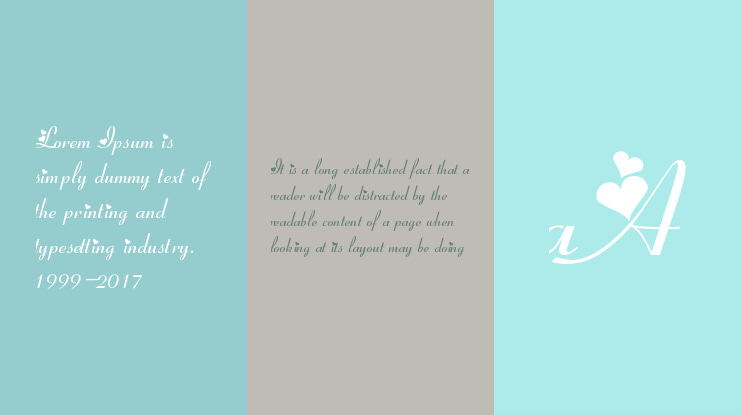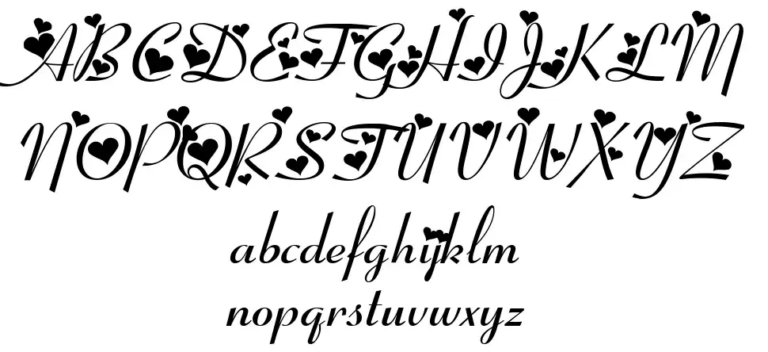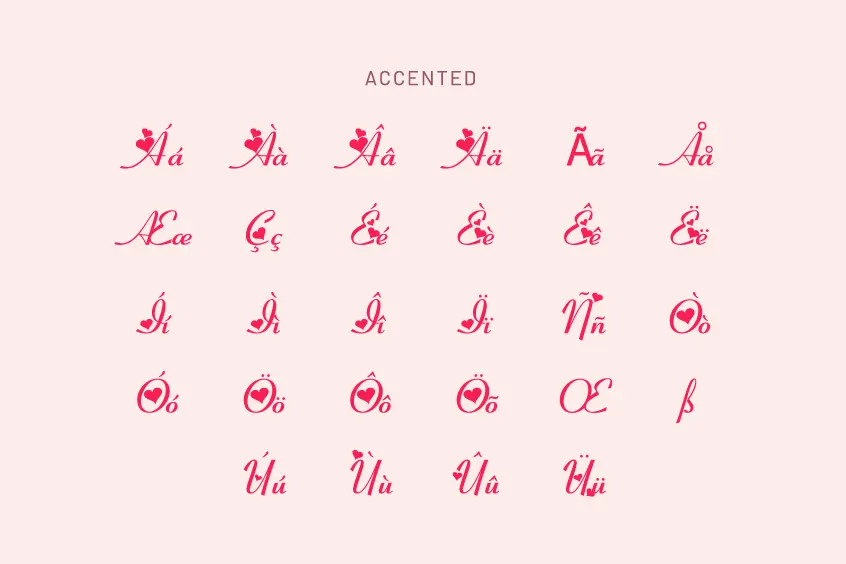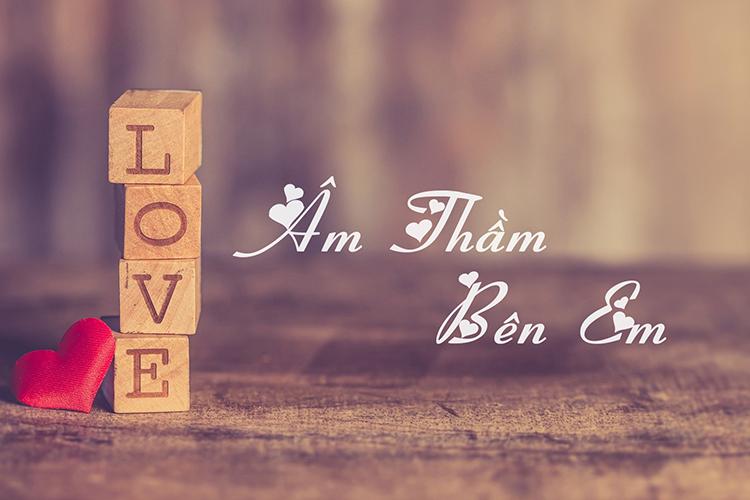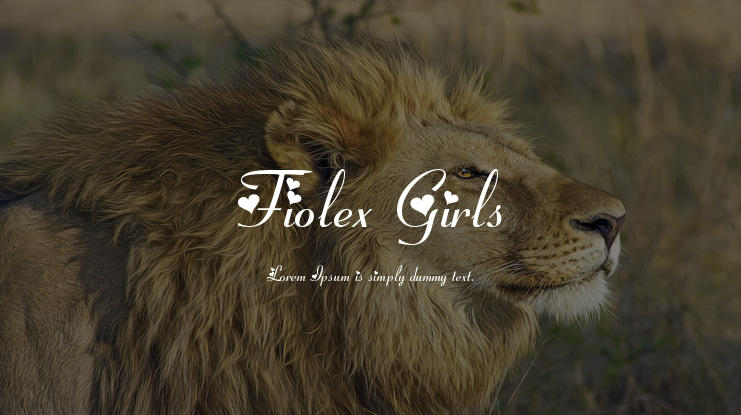
Đặc điểm thẩm mỹ độc đáo của Font UVF Fiolex Girl
Fiolex Girl không đi theo khuôn mẫu của các dòng phông chữ viết tay thông thường; nó tạo ra một ngôn ngữ thị giác ngập tràn cảm xúc tình yêu và sự vui tươi.
Họa tiết trái tim lãng mạn gắn liền trong từng con chữ
Đặc trưng lớn nhất của Font UVF Fiolex Girl là các dấu chấm trên đầu những chữ cái như ‘i’, ‘j’ hay các nét móc đuôi uốn lượn được thay thế bằng hình ảnh trái tim cách điệu ngọt ngào. Chi tiết độc đáo này giúp dòng tiêu đề của bạn ngay lập tức truyền tải thông điệp về sự nâng niu, chăm chút và tràn đầy tình cảm, cực kỳ phù hợp cho các sản phẩm quà tặng tình nhân, quà sinh nhật hoặc phụ kiện trang sức nữ tính.
Nét chữ viết tay mềm mại và bay bổng
Cấu trúc của font Fiolex Girl Việt hóa sở hữu những đường cong lượn sóng tự nhiên, độ nghiêng nhẹ nhàng tạo cảm giác như một lá thư tay được chấp bút nắn nót. Nhịp điệu chữ trôi chảy, thanh thoát mang lại diện mạo mộc mạc nhưng vô cùng duyên dáng, giúp bao bì sản phẩm của bạn dễ dàng chiếm trọn trái tim của các khách hàng yêu thích sự ngọt ngào.
Ưu điểm nổi bật của bản font Fiolex Girl Việt hóa
Khi ứng dụng các phông chữ trang trí vào thị trường trong nước, sự chỉn chu về dấu câu là yếu tố quyết định đến tính thẩm mỹ của ấn phẩm:
- Khắc phục triệt để lỗi dấu tiếng Việt: Phiên bản tải font Fiolex Girl Việt hóa đã được đội ngũ UVF trau chuốt thủ công từng dấu câu. Các dấu sắc, huyền, hỏi, ngã, nặng được vẽ thanh mảnh, đặt ở vị trí cân đối so với thân chữ và các họa tiết trái tim, không gây cảm giác chắp vá hay làm rối mắt người đọc.
- Bảo đảm tính đồng nhất thương hiệu: Việc tải font Việt hóa UVF Fiolex Girl chuẩn giúp bạn tự tin dàn trang các câu slogan hay lời chúc tiếng Việt mà không lo hiện tượng lỗi ô vuông hay nhảy về font hệ thống khô khan.
04 Ứng dụng thực tế của font Fiolex Girl trong sản xuất bao bì tại Doozypack.vn
Sự ngọt ngào và lãng mạn của Fiolex Girl mang lại hiệu ứng thị giác đắt giá trên các dòng sản phẩm bao bì thực tế do Doozypack.vn sản xuất:
- Hộp quà tặng Valentine & Socola thủ công: Tiêu đề thương hiệu hoặc câu chúc in bằng font Fiolex Girl trên nắp hộp giấy tạo cảm giác lãng mạn và gia tăng giá trị cảm xúc cho món quà trao tặng.
- Hộp giấy đựng bánh ngọt (Bakery, Cupcake): Nét chữ đáng yêu kết hợp cùng tông màu Pastel mang lại diện mạo tươi vui, sạch sẽ và kích thích vị giác cho các tiệm bánh ngọt.
- Thiệp cưới & Thiệp cảm ơn đính kèm: Nét chữ viết tay điểm xuyết trái tim là lựa chọn hoàn hảo cho những lời nhắn nhủ chân thành, tạo ấn tượng sâu đậm trong lòng người nhận.
- Tem nhãn mỹ phẩm handmade & Nến thơm: Giúp các sản phẩm xà phòng thủ công, tinh dầu thiên nhiên toát lên vẻ đẹp mộc mạc và lành tính.
Lưu ý kỹ thuật khi in ấn với phông chữ nhiều nét uốn lượn trái tim
Việc sản xuất bao bì thực tế sử dụng các phông chữ có chi tiết trang trí như Fiolex Girl đòi hỏi sự am hiểu kỹ thuật chuyên sâu tại xưởng in Doozypack.vn:
- Kiểm soát độ sắc nét của họa tiết trái tim: Các hình trái tim trên đầu chữ cái có diện tích khá nhỏ. Khi in Offset hạt mực mịn trên giấy Ivory, bạn nên để size chữ tối thiểu từ 12pt trở lên để các hình trái tim không bị dính mực làm mất form dáng.
- Cẩn trọng khi gia công ép kim (Hot Stamping): Nếu bạn muốn ép kim nhũ vàng hoặc nhũ bạc cho tiêu đề font Fiolex Girl, designer cần đảm bảo các đường nối nét có độ dày tối thiểu 0.15mm để lớp nhũ bám dính chắc chắn, không bị bong tróc ở các khúc cua chữ.